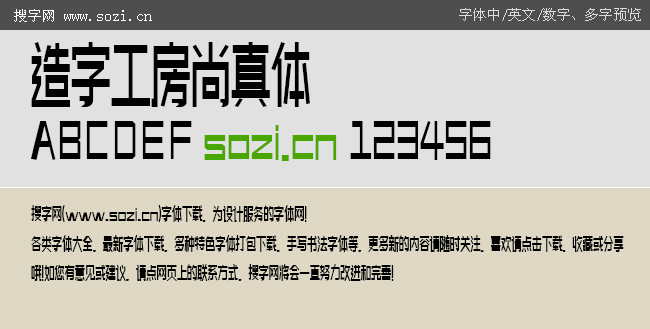
造字工房尚真體
搜字網(wǎng)給大家提供一款造字工房尚真體中文字體下載,造字工房尚真體筆觸較為粗實(shí),字形呈現(xiàn)細(xì)長(zhǎng)狀態(tài),具有很好的視覺(jué)影響力,適合應(yīng)用于藝術(shù)設(shè)計(jì)、平面宣傳設(shè)計(jì)、網(wǎng)頁(yè)設(shè)計(jì),海報(bào)設(shè)計(jì)等應(yīng)用。(本字體為個(gè)人非商用版,如需要商用請(qǐng)聯(lián)系官方購(gòu)買(mǎi)版權(quán))